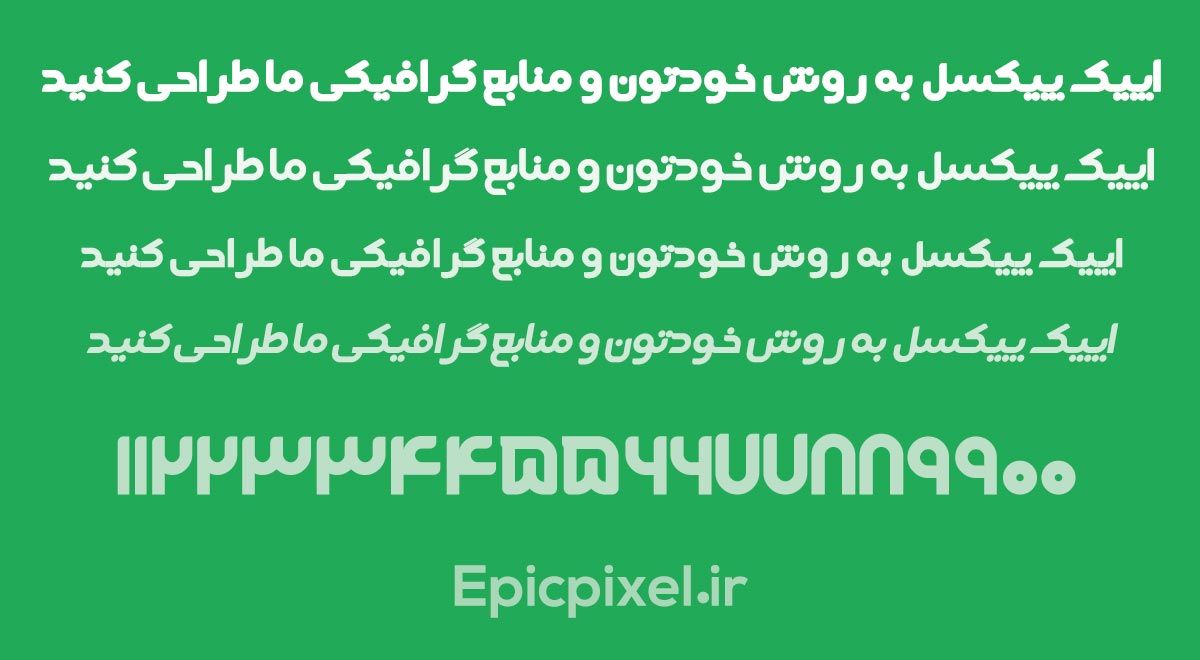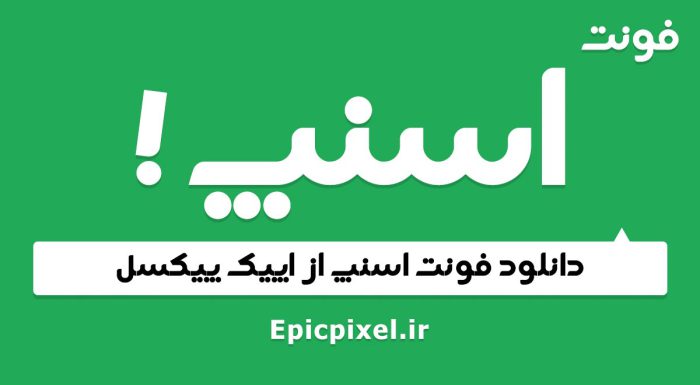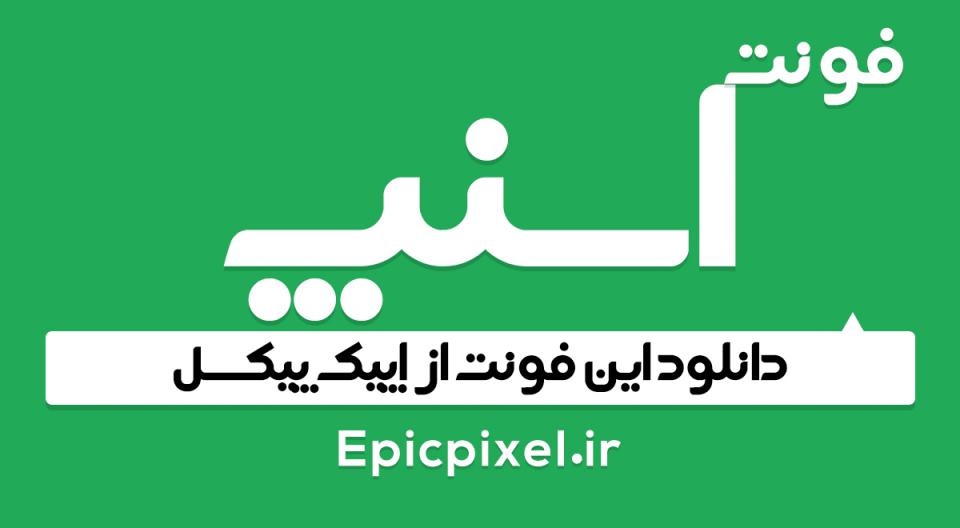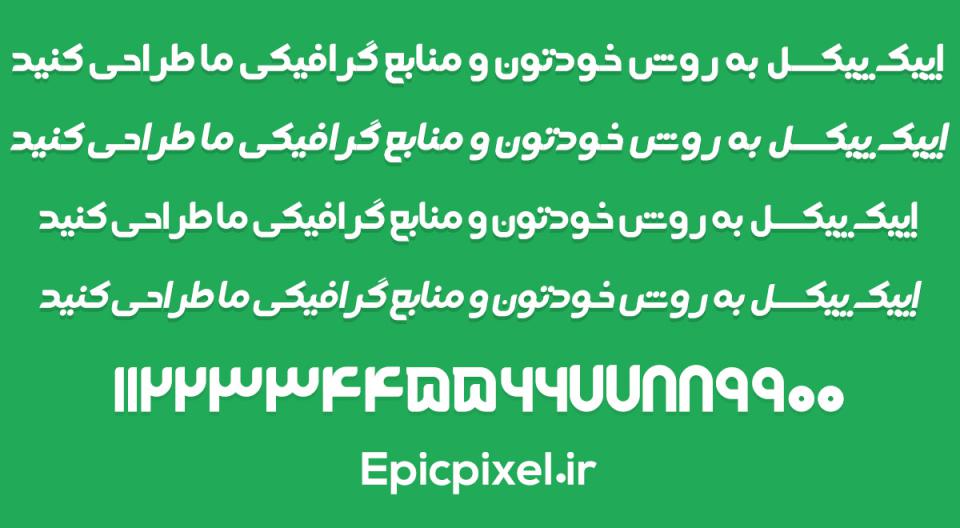
3 فونت اسنپ فارسی Snapp
فونت اسنپ، یک سبک نوشتاری فارسی برجسته و محبوب است که طراحی آن الهام گرفته از نشانه نوشتاری مجموعه اسنپ است. این فونت با فرم ضخیم و متمایز خود، ابزاری ایده آل برای خلق لوگوتایپ ها، عناوین چشم نواز و انواع کارهای گرافیکی محسوب می شود. نسخه رایگان این فونت معمولاً شامل دو ویرایش اصلی است و با فرمت استاندارد TTF ارائه می شود. نصب و استفاده از این فونت بسیار آسان بوده و در اکثر نرم افزارهای طراحی در ویندوز و اندروید (و برخی در iOS و مک) قابل اجرا است. ویژگی خاص این فونت، امکان تغییر شکل برخی حروف برای ایجاد زیبایی بصری بیشتر است.
فونت اسنپ: فونت بولد فارسی برای طراحی های خیره کننده (نصب آسان)
یکی از پرطرفدارترین سبک های حروف فارسی، فونت اسنپ است که با طراحی ضخیم و چشم نواز خود شناخته می شود. این فونت برای خلق لوگوتایپ های اختصاصی و متمایز بسیار کاربردی است. شکل و شمایل آن شباهت زیادی به نشانه نوشتاری مجموعه اسنپ دارد و الهام بخش طراحی آن بوده است.
این سبک نوشتاری در دو ویرایش عرضه شده که ویرایش تازه آن اخیراً منتشر گشته. بسته های دانلود رایگان اغلب هر دو ویرایش ۱ و ۲ (شامل به روزرسانی ها) را در بر می گیرند و امکان مقایسه و مشاهده ظاهر هر دو ویرایش در دسترس است.
فونت اسنپ به دلیل طراحی منحصر به فرد و وزن سنگین خود، گزینه ای عالی برای تایپوگرافی، طراحی پوستر و ساخت عناوین جذاب به شمار می رود. اگر به دنبال یک فونت چشم گیر و خاص برای پروژه های خلاقانه خود هستید، این سبک نوشتاری به شما پیشنهاد می شود. استفاده از آن نیازمند هیچ نرم افزار جانبی خاصی نیست و با فرمت رایج TTF قابل نصب و استفاده مستقیم در برنامه های طراحی است.
دانلودنسخه دوم و به روزرسانی شده این تایپ فیس به دلیل استقبال زیاد طراحان ارائه شد. در آپدیت جدید فونت اسنپ، تغییراتی در ساختار حروف و اضافه شدن دندانه ها به برخی از آن ها اعمال شده است که تفاوت هایی با ویرایش اول ایجاد می کند.
این فونت نوشتاری در آخرین بازطراحی خود با بررسی نسخه های قبلی، با تغییرات چشمگیر و بهبود یافته، به صورت کاملاً رایگان در دسترس قرار گرفته است.
بخش متمایز این فونت قابلیت تغییر ظاهر حروف است. حروف آغازین و میانی می توانند با استفاده از کاراکتر “ء” دگرگون شوند، در حالی که حروف پایانی با نگه داشتن کلید Shift و زدن “ء” تغییر می یابند. این امکان انعطاف پذیری بیشتری در چیدمان متن فراهم می کند. این فونت نوشتاری همچنین از اعداد و علائم نگارشی در زبان های فارسی و انگلیسی به طور کامل پشتیبانی می نماید. استفاده از این سبک فونت می تواند جلوه ای مدرن و خلاقانه به طرح های شما ببخشد.
کاربردهای فونت اسنپ در برنامه های گرافیکی
فونت اسنپ به دلیل فرم ضخیم و جذاب خود در طیف وسیعی از نرم افزارهای گرافیکی کاربرد دارد. در محیط ویندوز، می توان از آن در برنامه هایی مانند فتوشاپ (Photoshop) و سایر نرم افزارهای طراحی دسکتاپ برای طراحی پوستر، بنر، لوگوتایپ و عناوین بهره برد. کاربران موبایل نیز می توانند این فونت را در اپلیکیشن هایی نظیر اینشات (Inshot) برای ساخت استوری و پست های شبکه های اجتماعی، یا متن نگار برای خلق عکس نوشته های فانتزی و احساسی به کار گیرند. همچنین در بسیاری از برنامه های گرافیکی موبایل دیگر که از فرمت TTF پشتیبانی می کنند، قابل استفاده است.